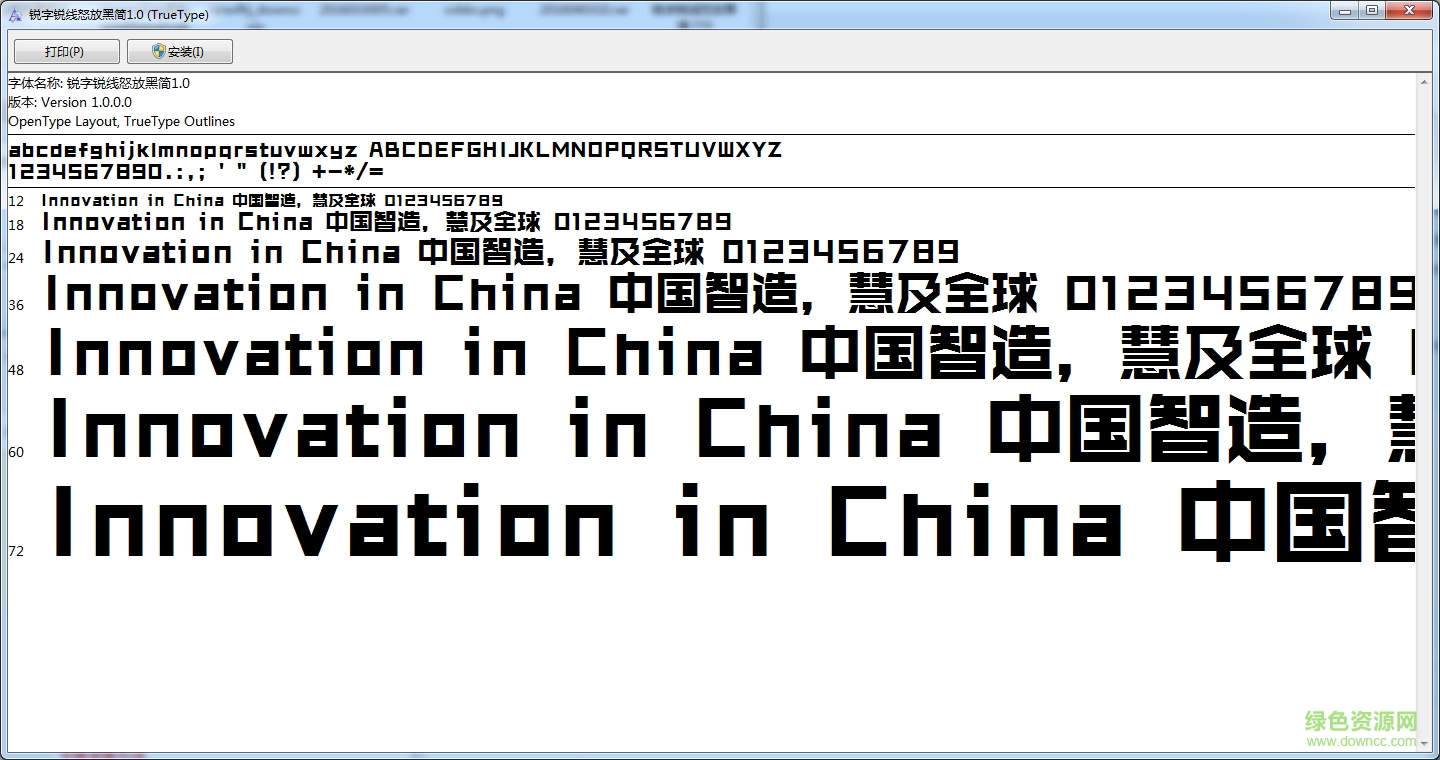
bigruixianblackgbv1.0字體又名銳字銳線怒放黑簡字體,是一款由銳字工房打造的特色字體,字體構(gòu)造極富創(chuàng)意,表現(xiàn)形式新穎,使用效果驚艷,需要的朋友快來下載吧!
字體設(shè)計運用夸張、明暗、增減筆劃形象、裝飾等手法,以豐富的想象力,重新構(gòu)成字形,既加強文字的特征,又豐富了標(biāo)準(zhǔn)字體的內(nèi)涵。
在設(shè)計過程中,不僅要求單個字形美觀,還要使整體風(fēng)格和諧統(tǒng)一,理念內(nèi)涵和易讀性,以便于信息傳播。